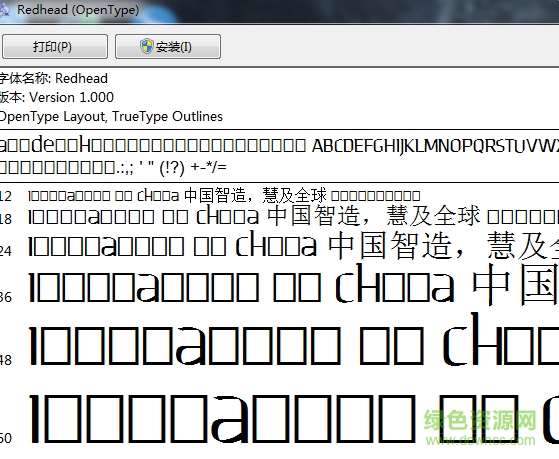
Redhead字體是一款超好用的個性英文字體,該字體可以廣泛應用于廣告設(shè)計、宣傳海報、ppt、影視制作以及任何使用文字的領(lǐng)域,有需要的朋友可以免費下載收藏。
Redhead字體是一款極具個性的字體,該字體十分飄逸,彰顯了自己的個性,有喜歡的朋友可以來綠色資源網(wǎng)下載使用!